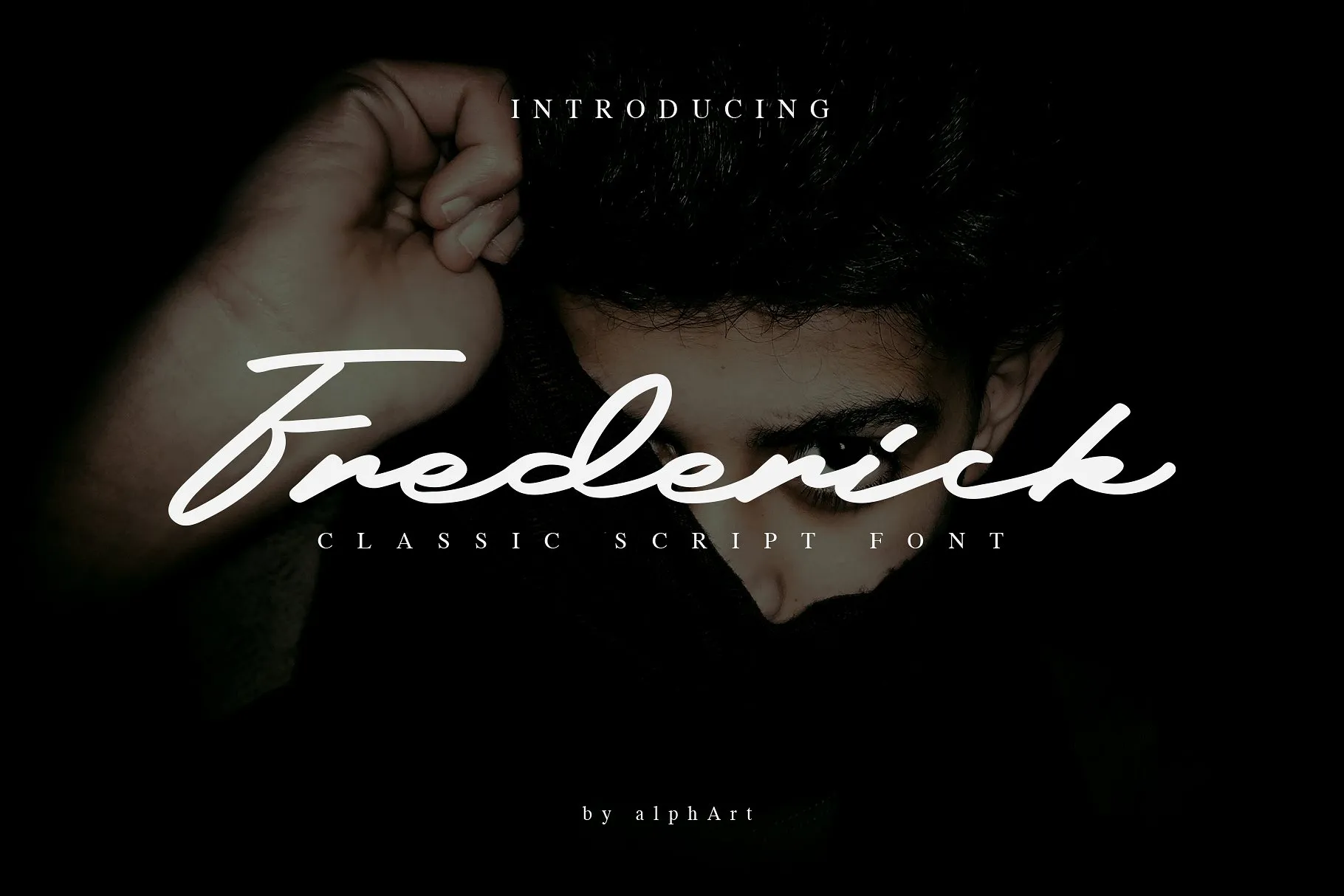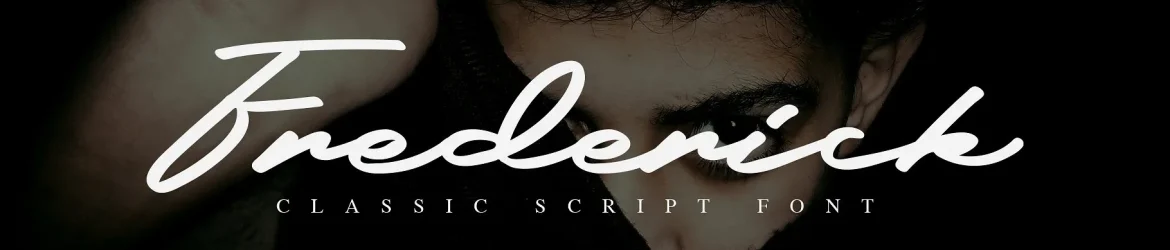
Frederick Script Font – Download Grátis
Aqui está uma versão com 2 parágrafos curtos para a descrição de download do Frederick Script Font: Frederick Script Font é um belo e elegante traço script feito à mão, perfeito para designers que estão procurando por uma fonte única. Com seu estilo simples e sofisticado, este traço é ótimo para projetos criativos variados. Através de sua versatilidade, você pode aplicá-lo em logotipos, impressões, websites e muito mais. Estamos certos de que esta fonte será a perfeita adição para seu portfólio. Este traço é o próximo passo em seu design de marca! Se estiver procurando por aquela fonte única que todos estão buscando, Frederick Script Font é sua fonte ideal. Engane-se e deixe-se maravilhar com a facilidade com que essa beleza tornará suas criações chamativas.